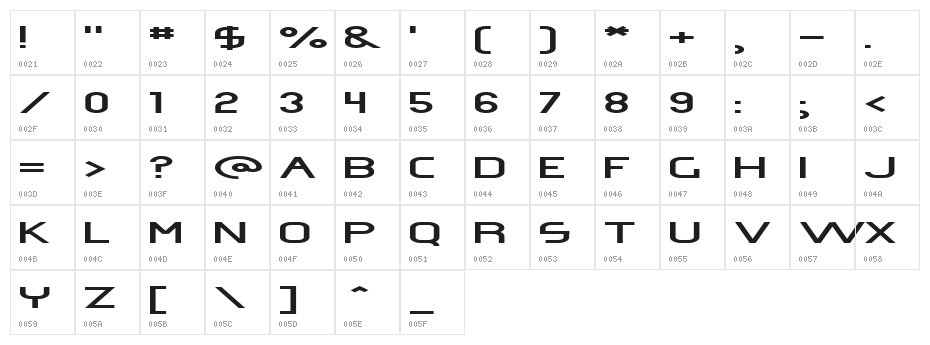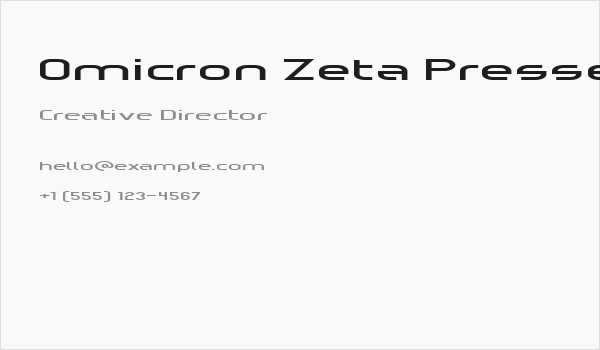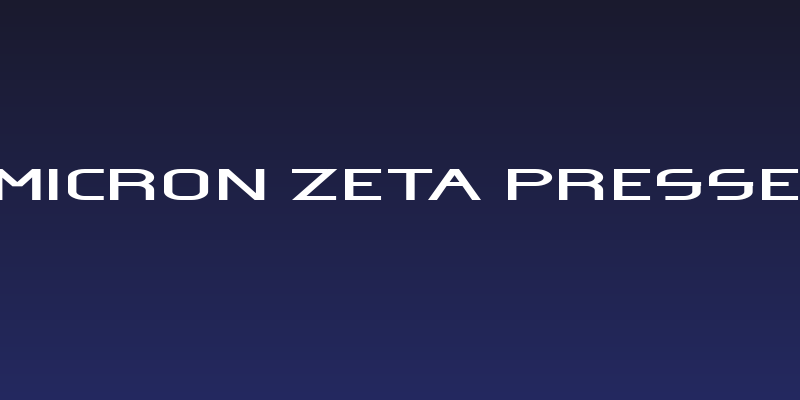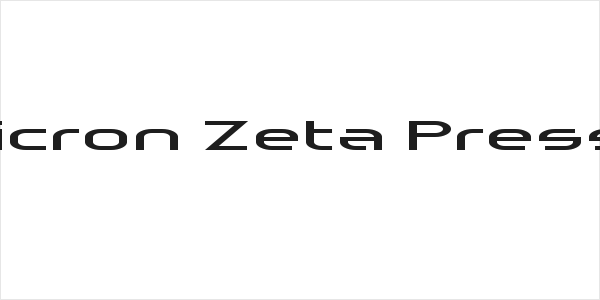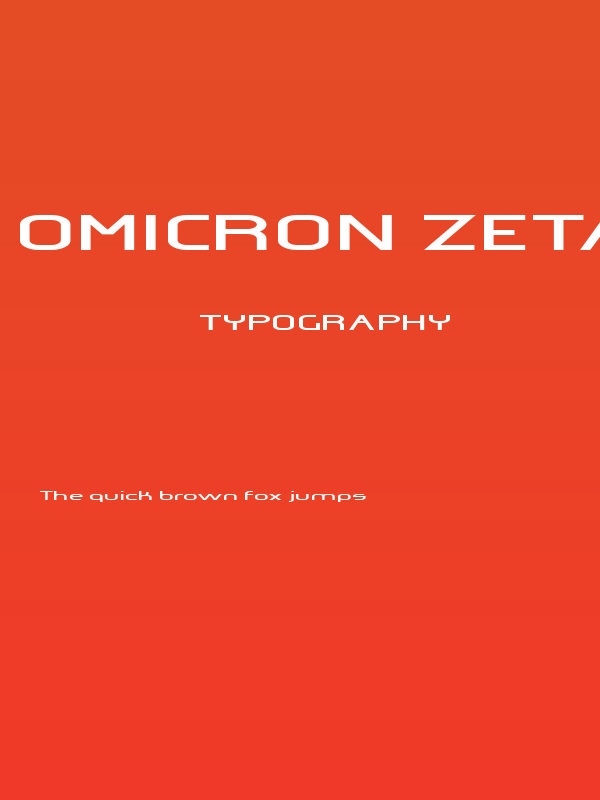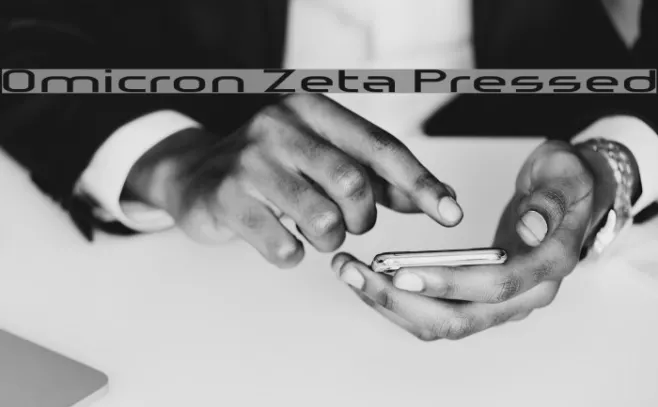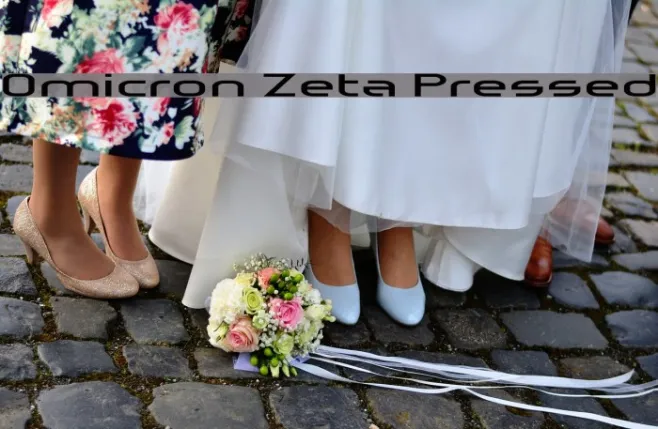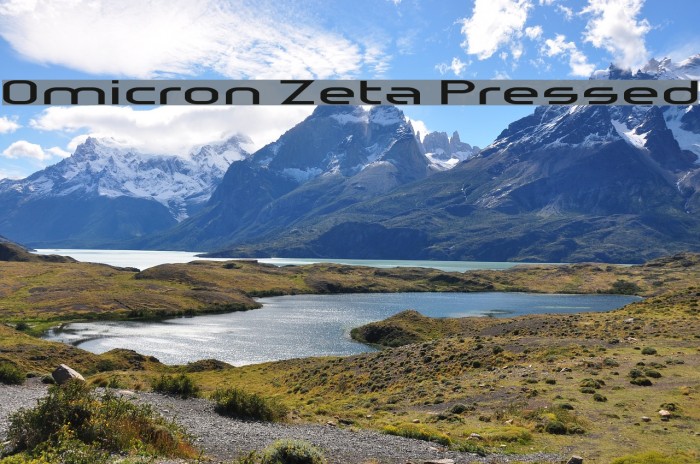
Omicron Zeta Pressed Font
| Anwendungsfall | Headlines, Logos, Digital Interfaces |
| Vorgeschlagene Projekte | Ideal for technology branding, modern web design, corporate presentations, and digital interfaces. |